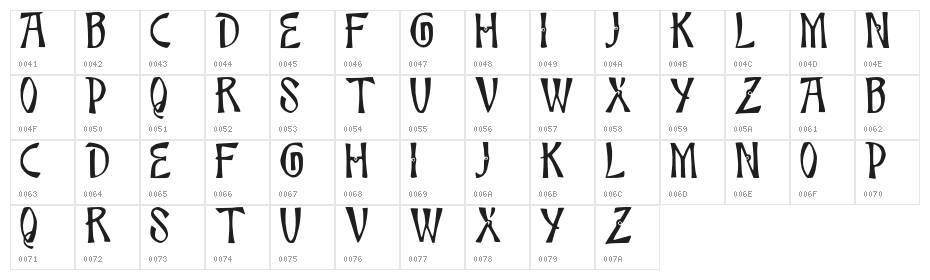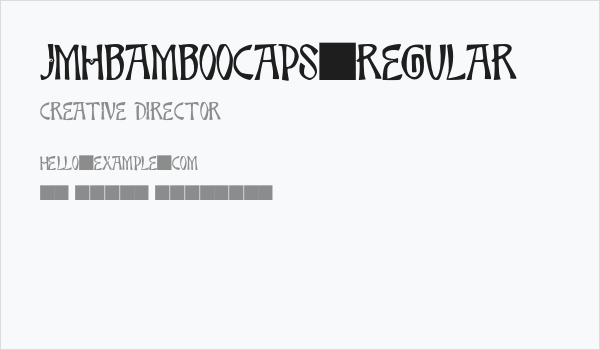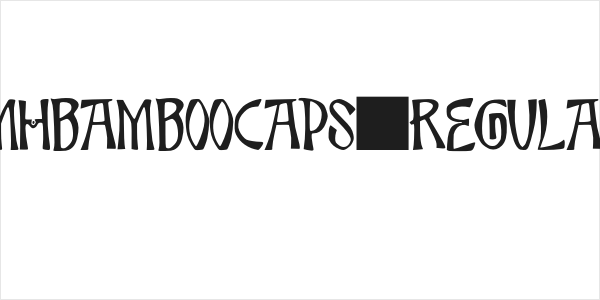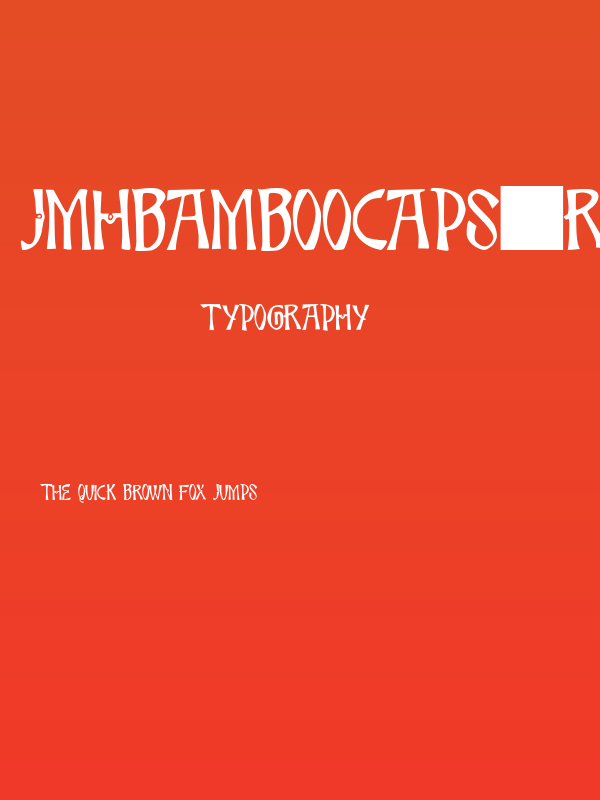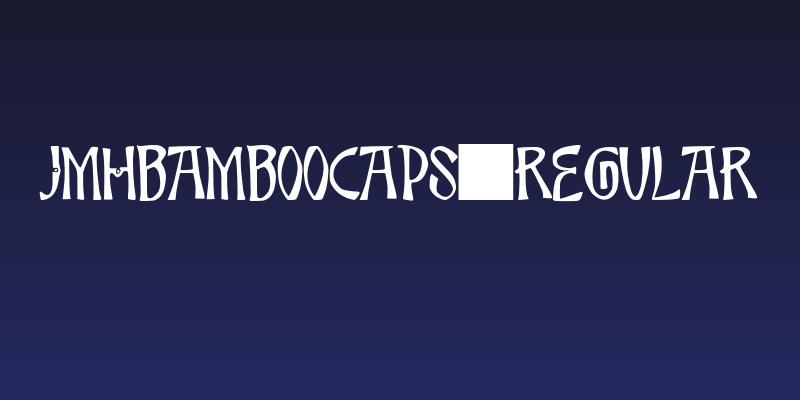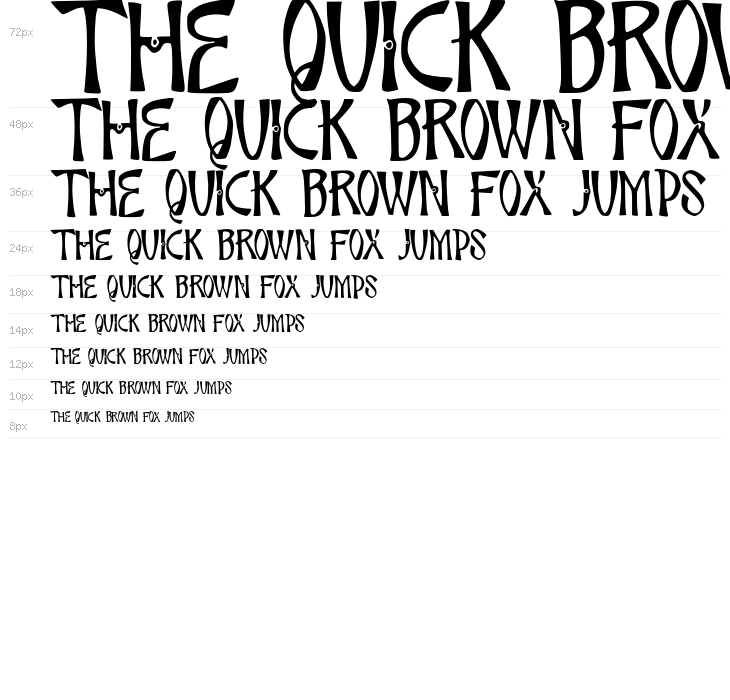
JMHBambooCaps-Regular Font
✎ Kids
| 分类 | Kids |
| 使用场景 | Logos, Headlines, Posters |
| 推荐项目 | Ideal for eco-friendly branding, children's book covers, nature-themed posters, and creative packaging designs. |